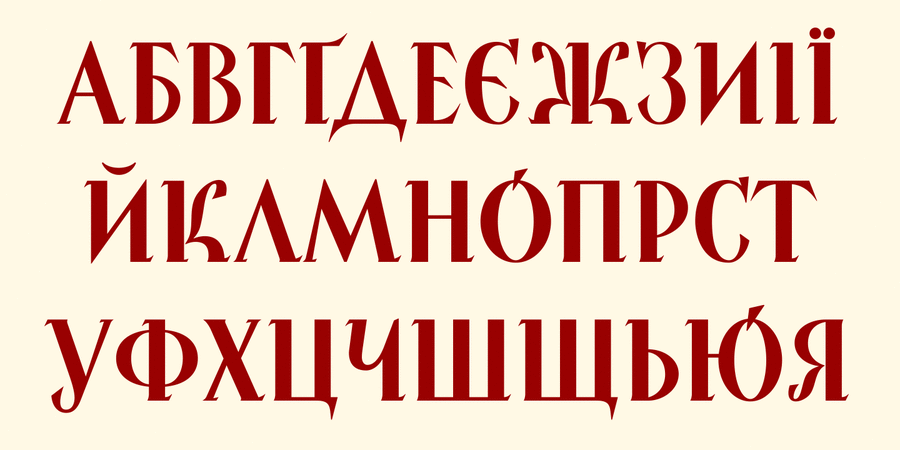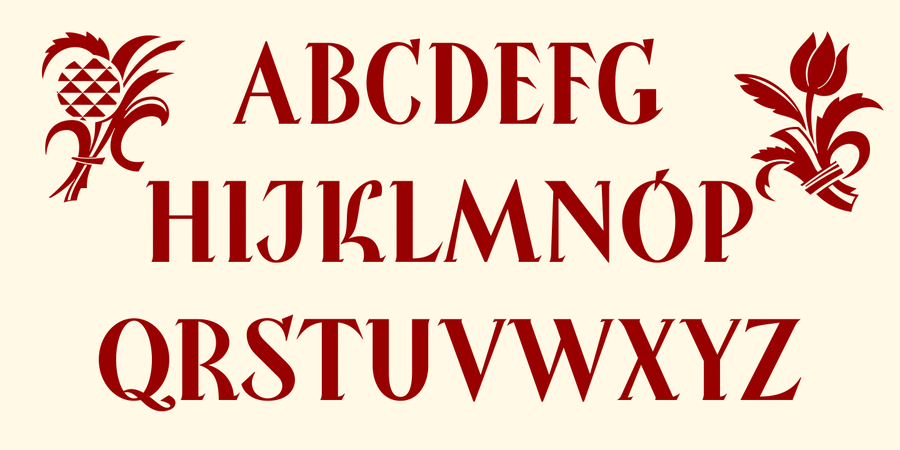
Шрифтова пара з Excentra Pro Light (1 з 2)Опис шрифта KalynaШрифт Калина відрізняється оригінальними стилістичними особливостями, наприклад асиметричними зарубками. Така конструкція характерна для українського стилю. Малюнок шрифту заснований на ескізах відомого українського художника-графіка початку XX ст. Георгія Нарбута. На його роботах базується ціла школа в українському образотворчому мистецтві, дуже впливова по сьогоднішній день. Гарнітура містить прописні знаки та орнаментальне зображення. Шрифт Калина розроблений у студії 2D Typo Олександрою Александровою та Лук'яном Турецьким у 2014 році.
Особливості сімейства шрифтів KalynaХіт десятиліття:
Хіт 1910-х Хіт 1920-х Близький історичний оригінал:
Асоціації з сімейством шрифтів KalynaОсобистість і характер гарнітури:
гострий, сміливий, самобутній, характерний, оригінальний, вільний, різкий, етнічний, натуральний, традиційний, старовинний, козацький, вольний, гордий, дотепний, колоритний, артистичний, художній, дерев'яний, пивний, історичний